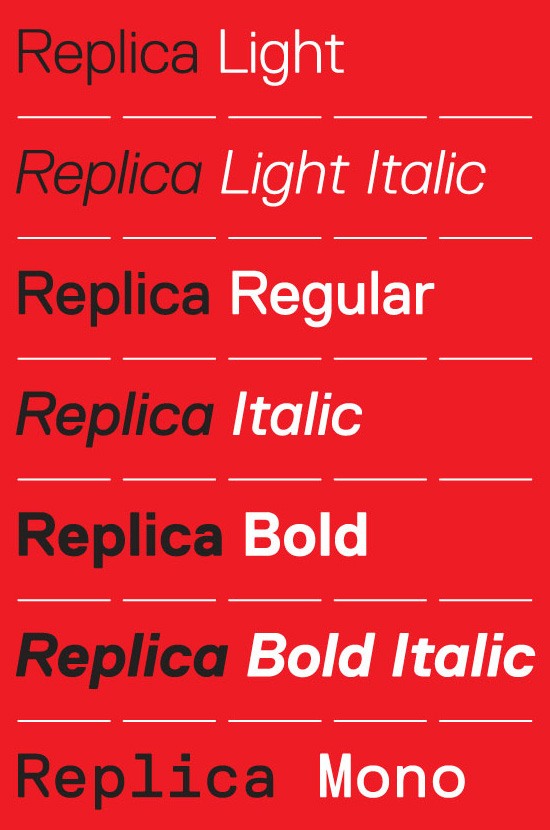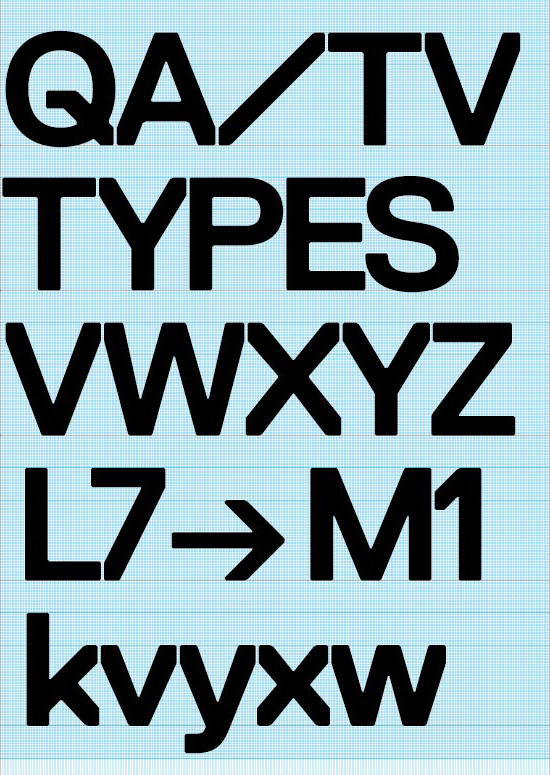
Replica (Lineto)
Replica is a new sans serif typeface conceived and designed by Zurich-based design studio Norm. It is intended for use as text face as well as for more graphic applications like headlines, signwriting, etc.
Replica was designed on a very reduced and religiously strict grid which defined each and every design decision. In place of the 700 units for standard caps height in Fontlab, the grid was reduced to just 70 units. This arbitrary simplifaction and self-induced restriction strongly influences the shape of each individual glyph.
Further significant characteristics are the bevels on inner and outer corners which visualise the limitations of the grid and which function as a sort of negative ink trap, something that is facilitated by today’s sophisticated precision printing technologies. Another defining attribute is the vertical cuts of diagonals which enables users to set Replica very tightly, especially in the «Bold» and the «Heavy» weights.
These specific properties of Replica result in a typeface that has all the features of a classic sans serif font of middle-european descent, while the font is a beautiful antithesis of the notion of «Vorsprung durch Technik» by exposing its genetically modified DNA.
The LL Replica font family is released in two stages:
The first offering includes the 6-weight Family Package (Light, Light Italic, Regular, Italic, Bold, Bold Italic) and a separate Monospace cut in the Regular weight.
A caps-only «Heavy» cut, an ultra-thin «Laser» cut and two «Antique» cuts (Regular and Italic) are scheduled for release on 1 November 2008 along with the OT versions of all other weights, while a Cyrillic version is still in the works.
die bold sie wie eine zugeschmierte oder im bleisatz gedruckte medium aus.
ich weiss nicht ... auf anhieb nicht so mein ding. ich finde es zunehmend auch immer
uninteressanter den buchstaben auf zwang irgendwelche details zu geben.
wie hier die abgeschnittenen vertiaklen. das wirkt so al wölle man sagen "dieser font hat
was ganz besonderes und eigent sich dadurch gut für logos, headlines ..."
Ich finde es ist für Norm eine sehr typische Schrift.
Ein Konzeptbzw. Raster wird durchgezogen und
dadurch klemmt es hier und da etwas - hat aber genau
deshalb seinen Reiz wie ich finde. Siehe Normetica
oder Simple ...
finde nicht das man diese schrift mit normatica oder simple vergleichen kann.
das sind spezielle fonts die durch ihre technische aber saubere (!) schönheit
begeistern. das hier sieht auf den ersten blick nach einer zu fett gedruckten akkurat aus.
für ein CD zu unsauber. für eine textschrift zu speziell. vorallem diese künstliche fette stört
mich. ich hätte nichts gegen eine akkurat mit diesen details, als alternate version. aber so?
Schau dir die Details der Simple an - die basiert
ebenfalls auf einem sehr straighten Raster und
bricht dadurch mit gewissen optischen Regeln.
Bei den Übergängen der Kurven in die Geraden ist
beispielsweise nichts optisch angepasst.
Die Replica wirkt sicher etwas kruder aber das
Prinzip des Rasters ist sauber durchgezogen.
Die Jungs nennen sich ja nicht umsonst NORM.
Ich bewundere ja die Länge des PR-Textes. Ich wüsste gar nicht, was ich zu einer solch langweiligen Schrift alles schreiben sollte … :bandit:
die simple ist ein ganz anderer fall. sie wirkt durch ihre technischen charakter sympathischer.
der nehme ich auch diese "unangepassten optischen eigenheiten" ab. als käme sie frisch
aus nem terminaldrucker.
aber ich habe kein problem wenn dir die replica gefällt. :schonklar:
geschmäcker sind verschieden – ich finde es halt nur zu offensichtlich das sie 'eigen' wirken
soll. vielleicht finde ich aber auch keine schublade für den font. der name passt ja schon,
irgendwie. bei anderen schriften geht mir das aber in letzter zeit ähnlich.
hängt vielleicht auch von meinem momentanen geschmack ab.
hmm. so in versalien siehts auch schon wieder anders aus.
Habe ich mir auch grade gedacht.
Hach, das hat schon was, wenn die abgeschnittenen Diagonalen sich so schön zusammenfügen. Aber findet ihr nicht auch, dass beispielsweise das Versal-S ein wenig wacklig da steht. Und wo hier schon die Akkurat als Vergleich dient: ich finde die Bögen/der Bauch der Versal-P bei beiden Schriften irgendwie zu breit.